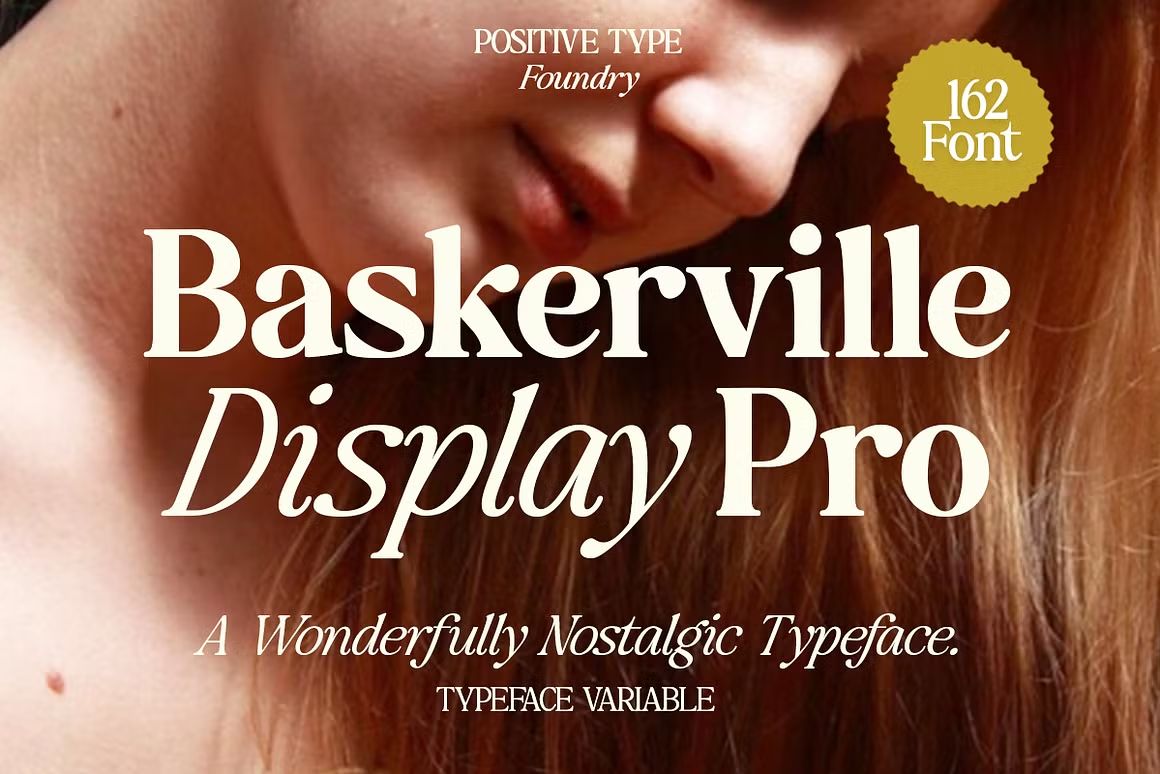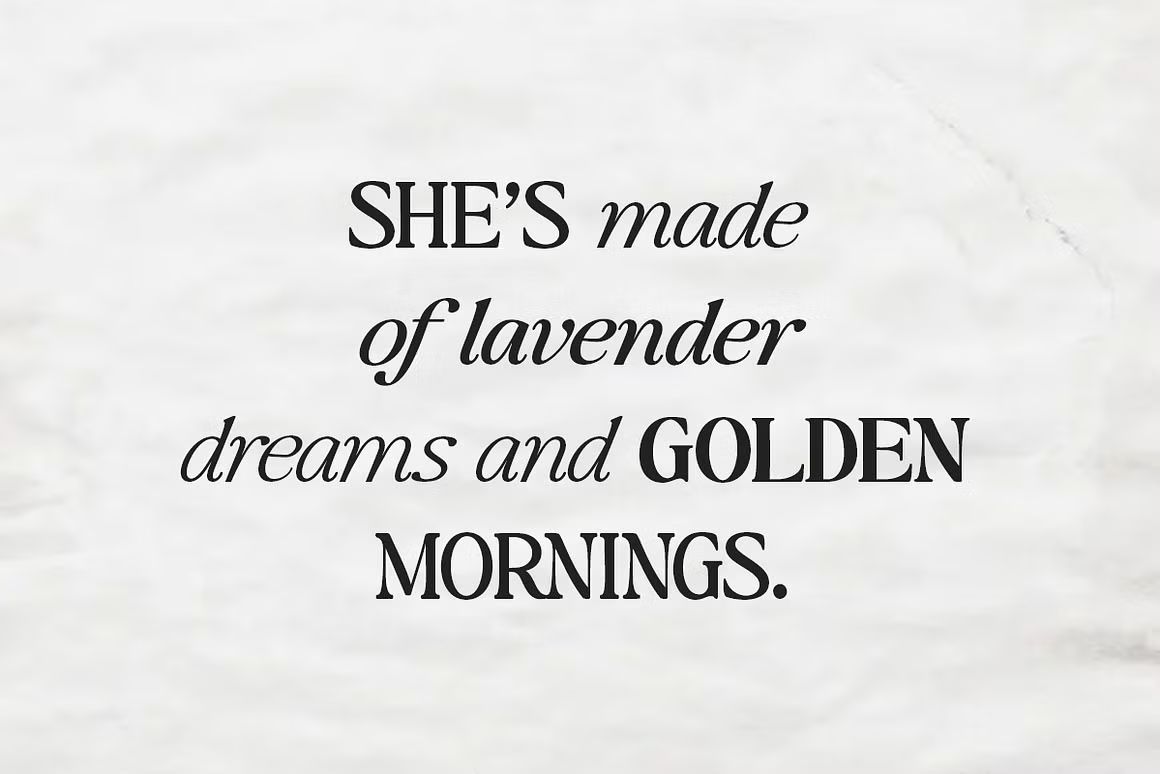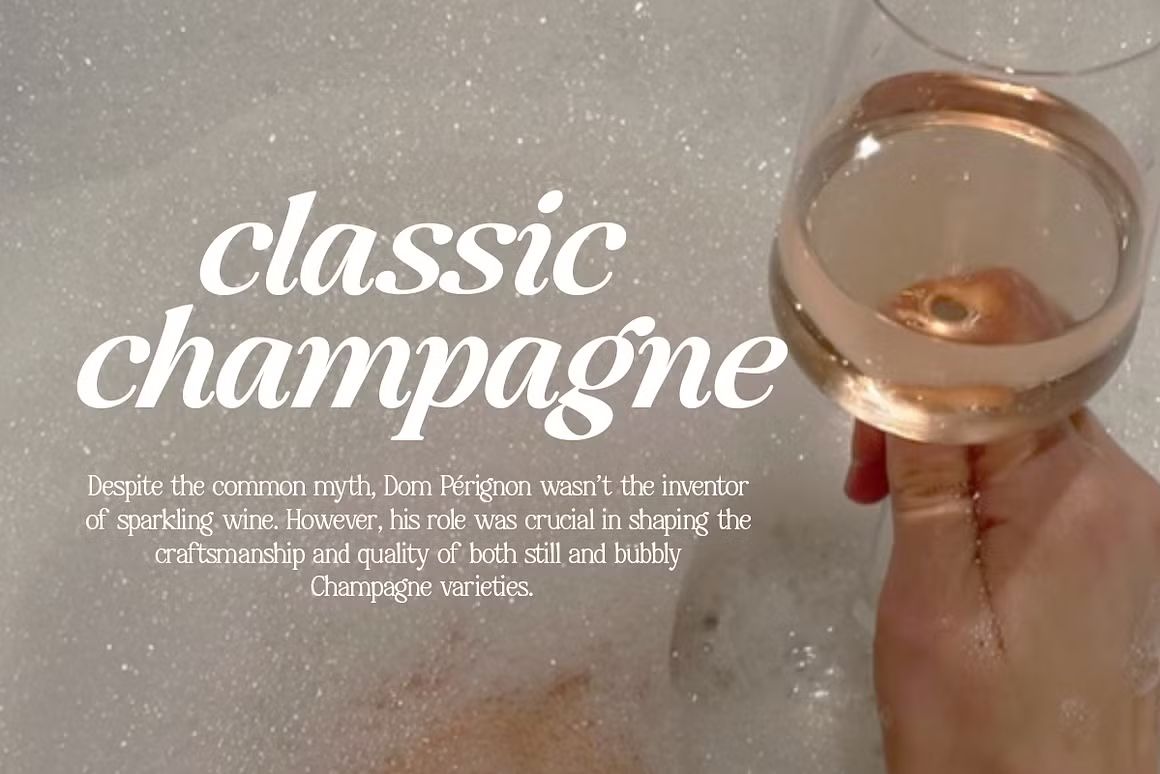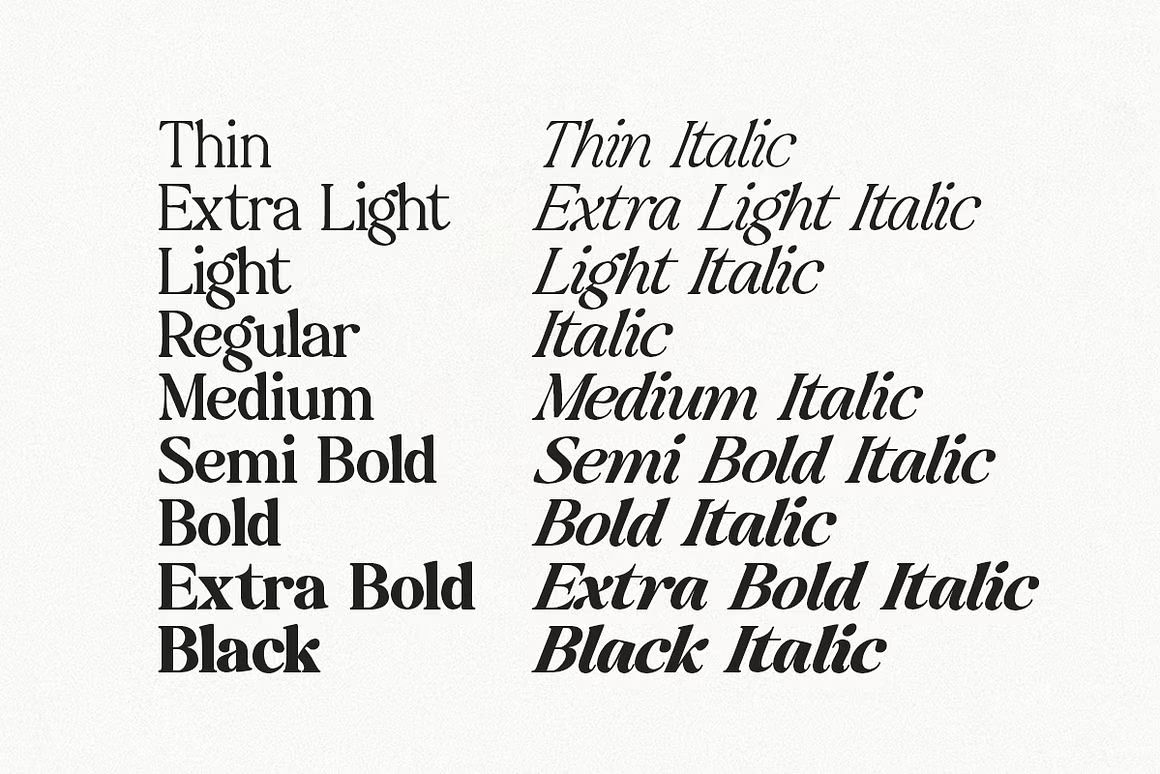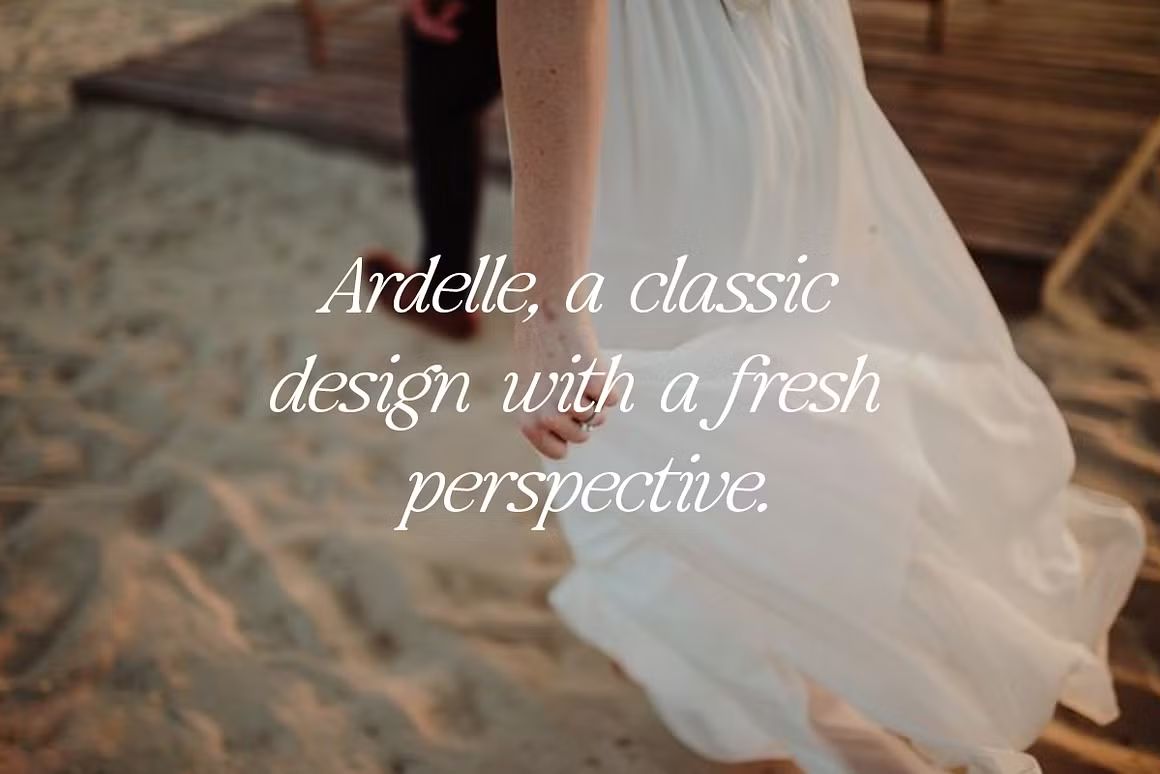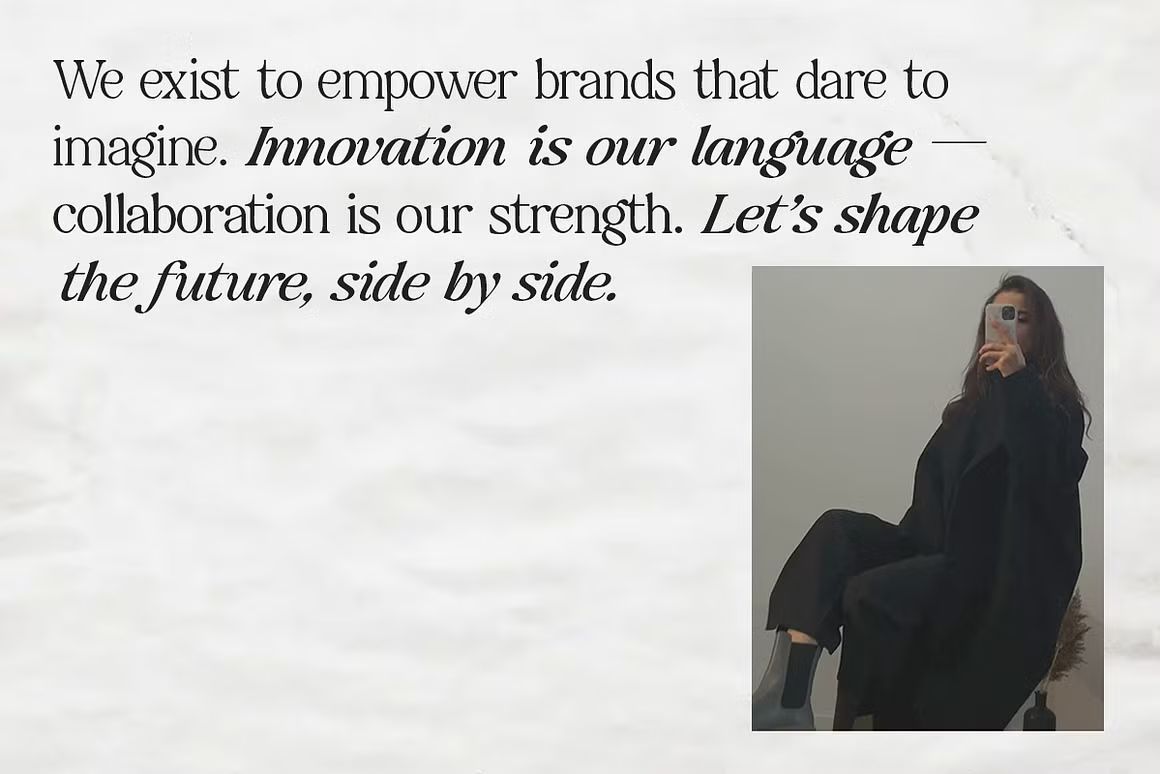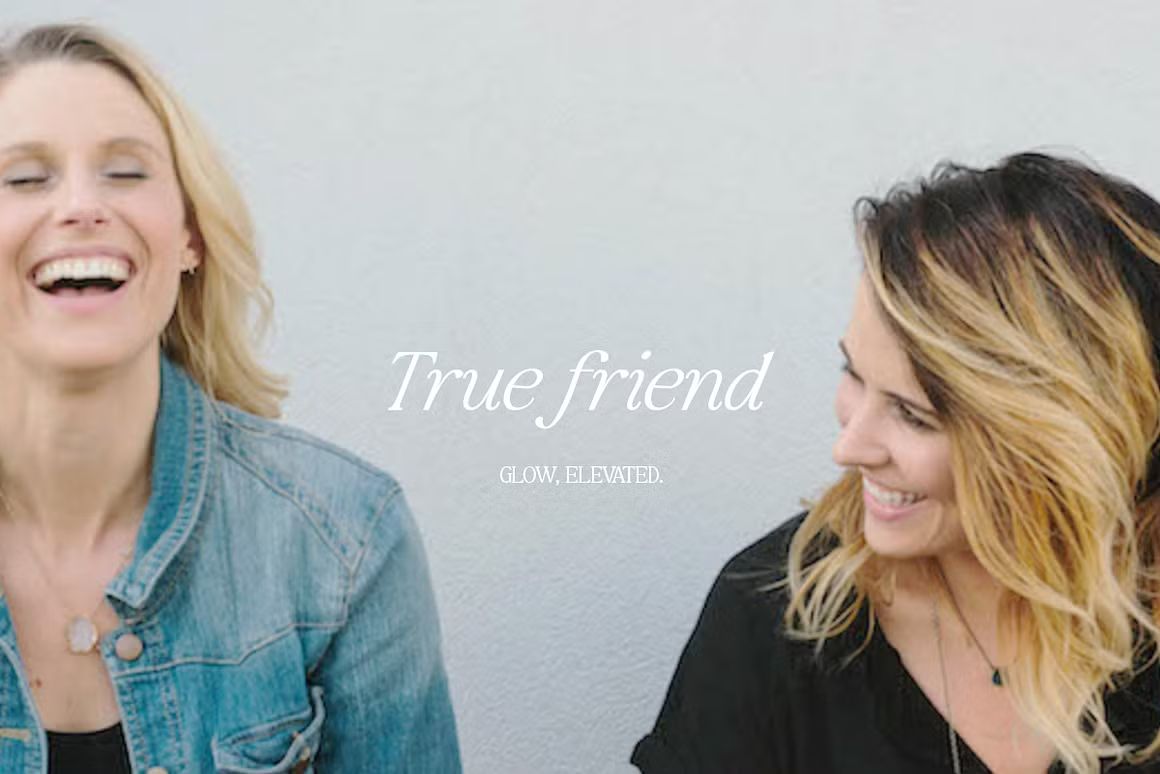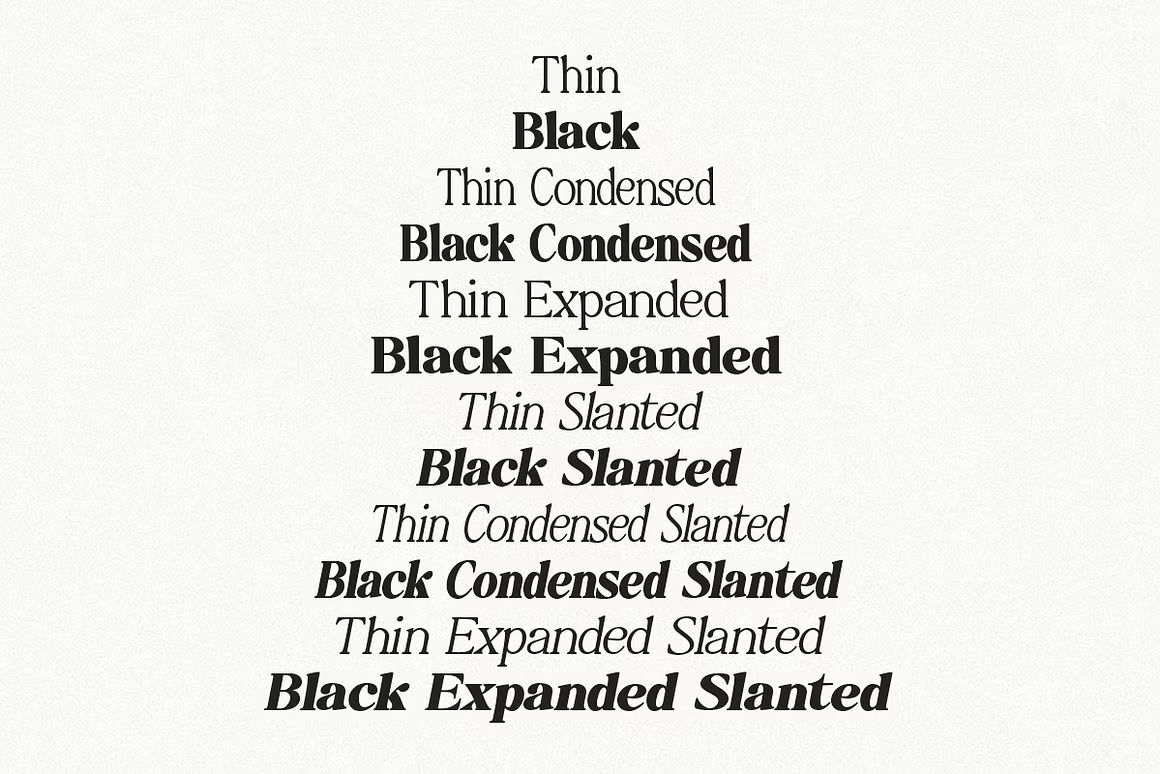
Baskerville Display Pro – Sans Serif Font
Baskerville Display Pro adalah versi modern dari font serif klasik yang dirancang khusus untuk tampilan besar seperti headline, editorial, dan desain mewah. Dengan kontras tinggi, serif yang elegan, dan bentuk huruf yang anggun, font ini memberikan kesan refined, klasik, dan profesional. Cocok untuk editorial, branding premium, packaging, dan desain cetak bergaya elegan.
• Serif klasik dengan sentuhan modern untuk tampilan besar
• Ideal untuk editorial, branding, dan judul mewah
• Termasuk huruf kapital, kecil, angka, dan simbol